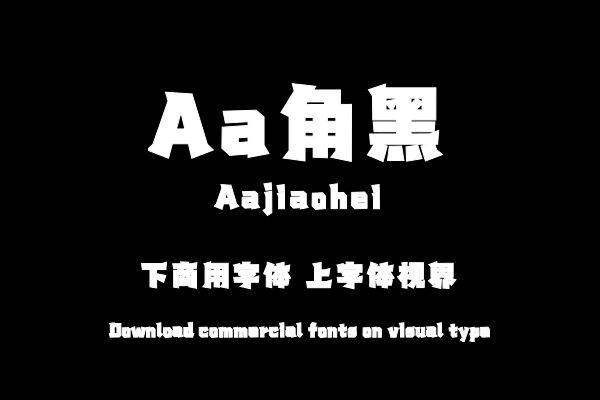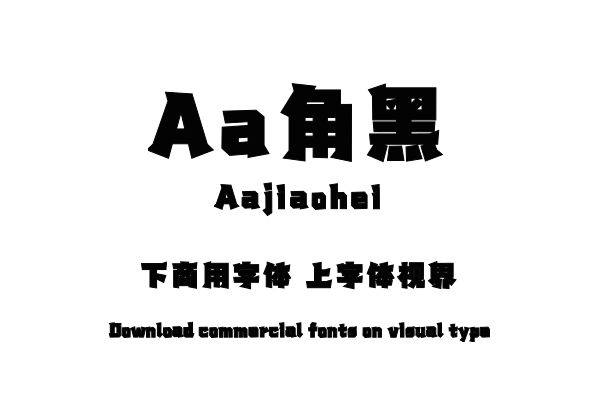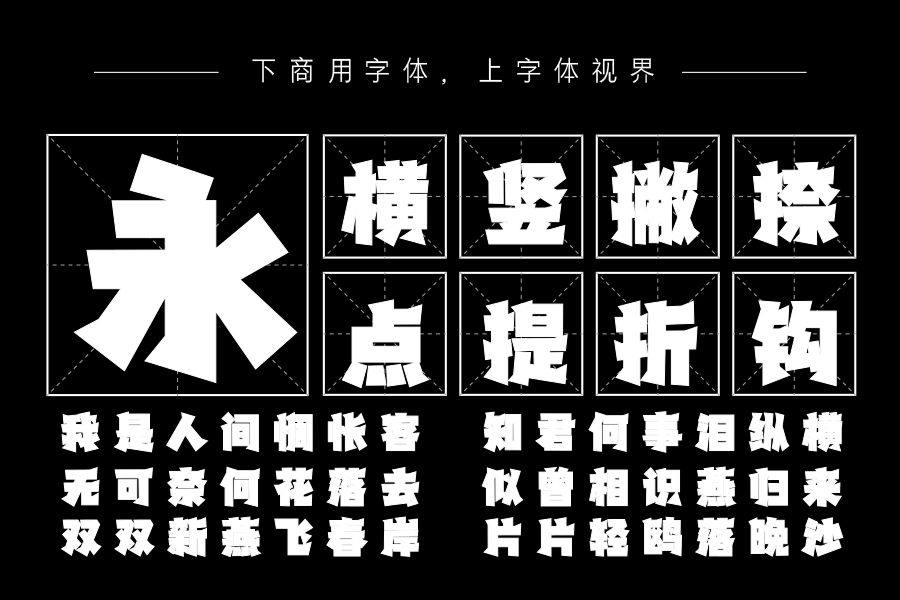
字的结构方正厚重,笔画简洁有力,使字体更具力量感,三角形的装饰角和笔画灵活了字体的空间又增加了趣味性和现代装饰感。是一款超粗的简洁有力的创意标题黑体,适用于各种......购买须知:“下载服务费”与“字体VIP”所获得字体 仅用于个人非商用, 商用请联系付费授权。本字体为电脑用字,手机没有root权限不支持直接手机换字(手机如何root,请自行百度搜索教程)。购买前请先 了解清楚后再付款 ,字体为虚拟产品无法回收 一旦购买不支持退款。